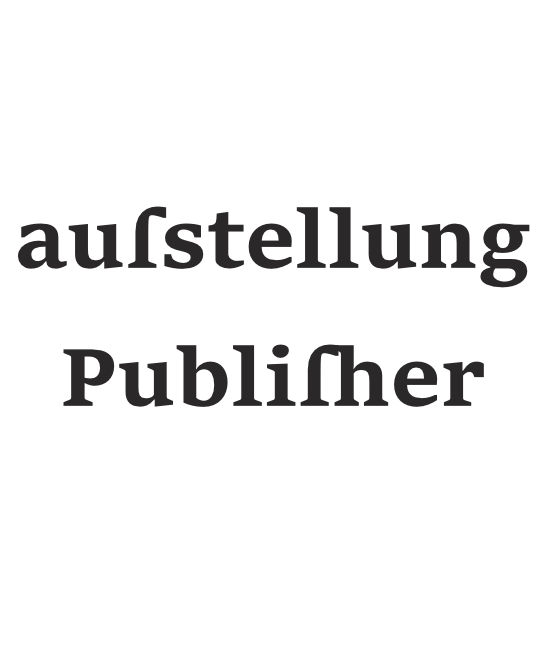
Historische (Schrift)Zeichen
Rein aus privaten Interesse besteht meine Freizeit aus Foto- und Grafikgestaltung, sowie das Erstellen von Druckmaterialen aus früherer Zeit. Das sind Plakate (Kino, Film, Politikgeschichte usw.).  Als Retro- und Vintageliebhaber bin ich vernarrt in alten Illustrationen, Zeitschriften und sämtlichen Gestaltungsmitteln (u.a. natürlich die Typografie), die dazu gehören!
Ich stöbere z. Zt. in einem sehr interessanten Buch („Propaganda des Terrors“ von Sylke Wunderlich), was sich ausgiebig mit der Gestaltung von Plakaten, Bildern, Hefte und anderen so genannten Propagandamaterial des NS- Regimes zwischen 1933 und 1945 beschäftigt.
Was mir dabei aufgefallen ist, dass auf vielen dort abgebildeten Plakaten historische Zeichen (bezeichne ich diese Glyphen richtig?), wie das lange s, angewendet wurden.
Ich habe es erstmal auf die Schnelle beim Font „Sitka“ im Affinity Publisher gefunden, auf einem meiner Rechner, der nicht so gut mit gebrochenen Schriften ausgestattet ist, und euch das angefügte Beispiel zum Verständnis hoch geladen. In der Fraktur oder Gotisch ist dieses "s" natürlich mit ausschweifender Unterlänge(?) versehen.
Meine Frage lautet: wird dieses Schriftzeichen heutzutage noch verwendet, wenn andere als die zeitgenössischen Schriften, wie „Tannenberg“, „Deutschland- Gotisch“, und Co. benutzt werden?